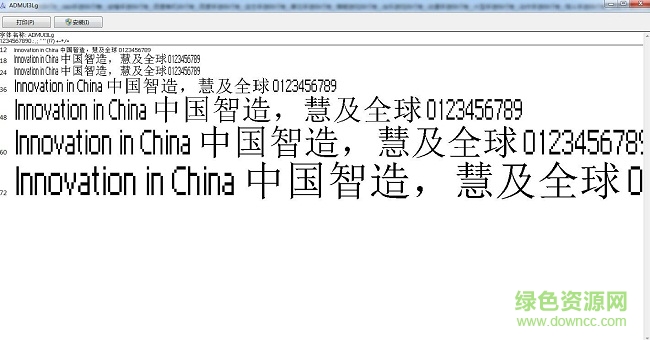
admui3lg常規(guī)體
admui3lg是什么字體?admui3lg常規(guī)體是一款fon格式的Windows系統(tǒng)字體,數(shù)字和字母顯示參差,自帶數(shù)碼感,適合科技主題,常常用在網(wǎng)頁設(shè)計(jì)、機(jī)械等領(lǐng)域,有需要者歡迎免費(fèi)下載!
現(xiàn)代字體風(fēng)格特點(diǎn)
現(xiàn)代字體設(shè)計(jì)趨于清晰簡潔,為迎合現(xiàn)代特征,字體設(shè)計(jì)被簡化,襯線逐漸被去除,線條也不再有粗細(xì)之分,干凈利落,更具機(jī)械繪制的特點(diǎn)。
admui3lg常規(guī)體
標(biāo)準(zhǔn)字體特點(diǎn)
經(jīng)過精心設(shè)計(jì)的標(biāo)準(zhǔn)字體與普通印刷字體的差異性在于,除了外觀造型不同外,更重要的是它是根據(jù)企業(yè)或品牌的個(gè)性而設(shè)計(jì)的,對(duì)策劃的形態(tài)、粗細(xì)、字間的連接與配置,統(tǒng)一的造型等,都作了細(xì)致嚴(yán)謹(jǐn)?shù)囊?guī)劃,比普通字體相比更美觀,更具特色。